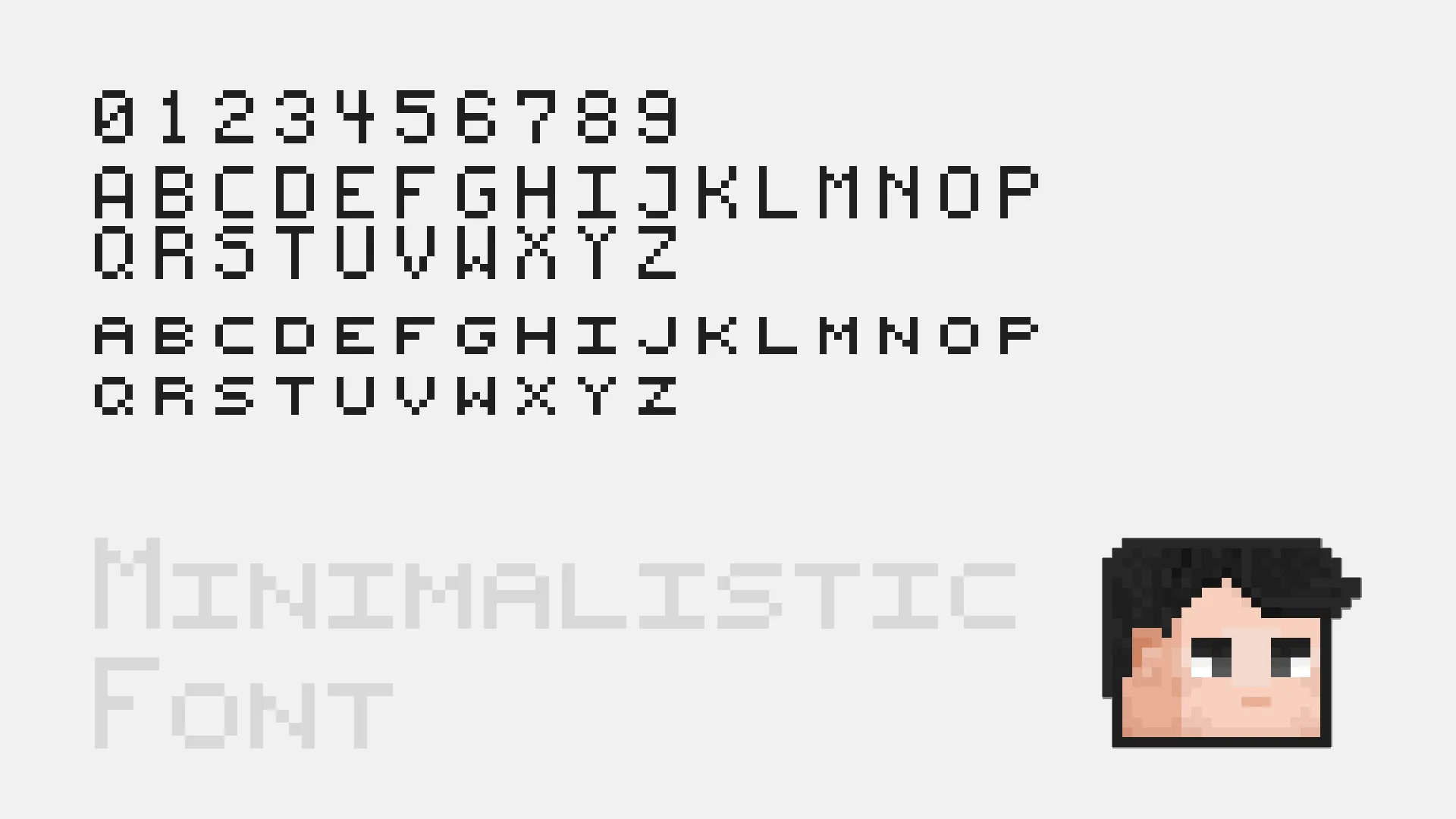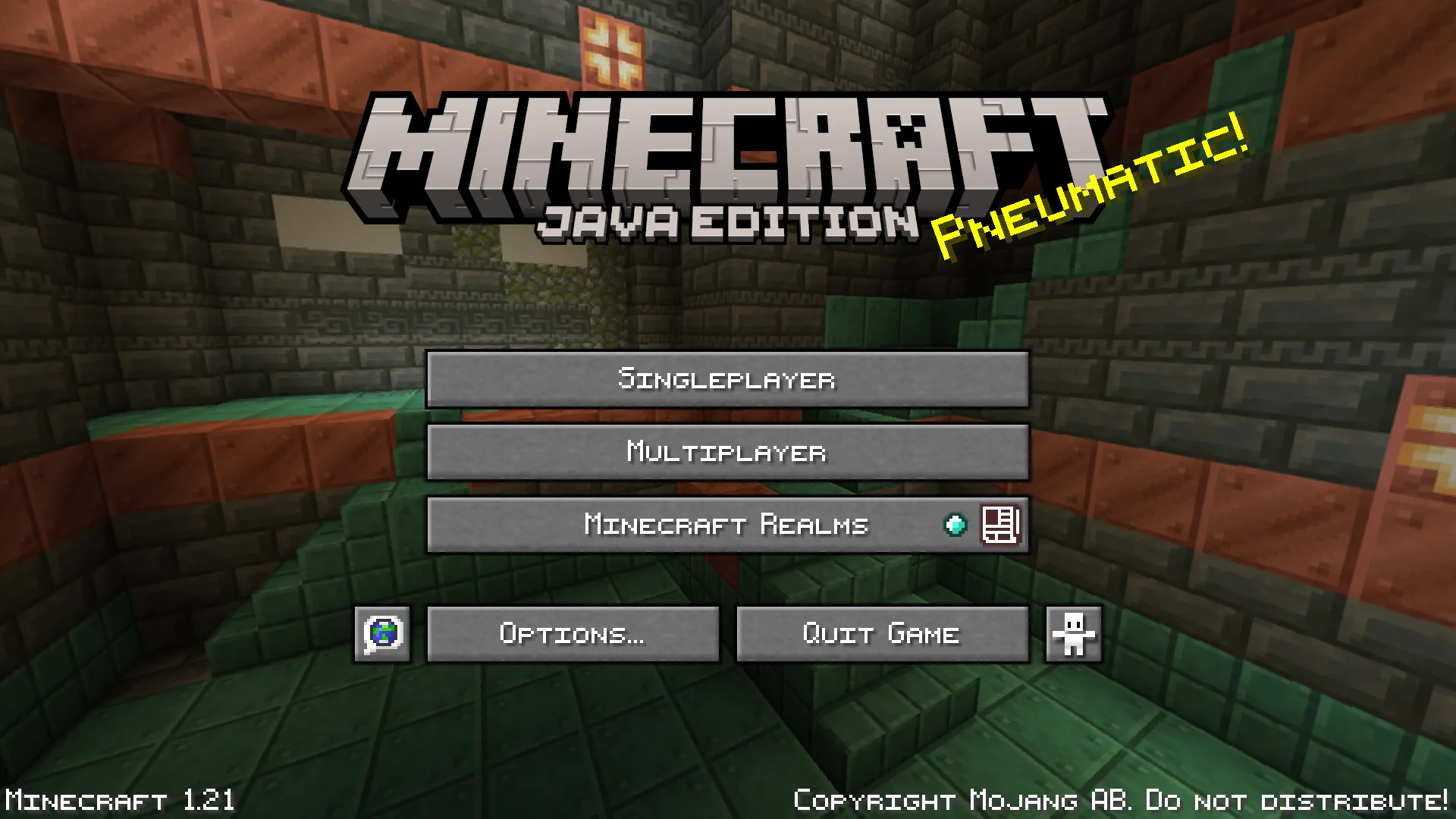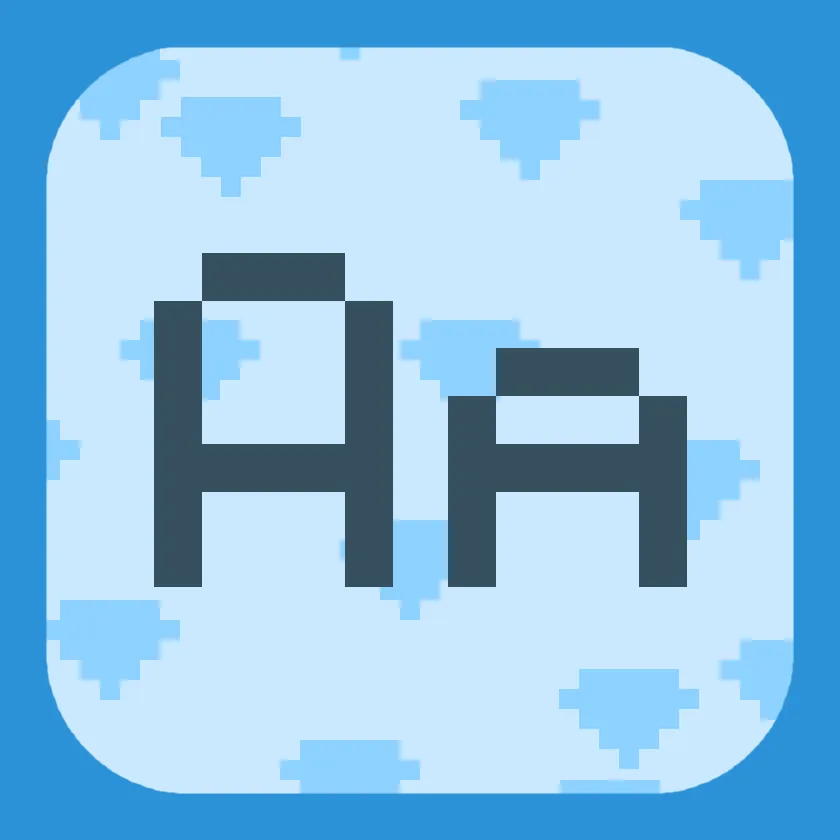
Minimalistic Font
Минималистичный шрифт для Minecraft, заменяющий стандартный на чистый и современный стиль, улучшающий читаемость текста в игре.
Этот ресурспак заменяет стандартный шрифт Minecraft на минималистичный, придавая игре современный эстетичный вид. Все текстовые элементы, от меню до внутриигровых сообщений, становятся стильными и легко читаемыми, что делает процесс строительства и исследования более приятным.
В настоящее время пакет поддерживает только английский текст, но в будущих обновлениях планируется добавление арабского шрифта. Он совместим с указанными версиями Minecraft и не влияет на производительность игры, сохраняя чистый и лаконичный стиль.